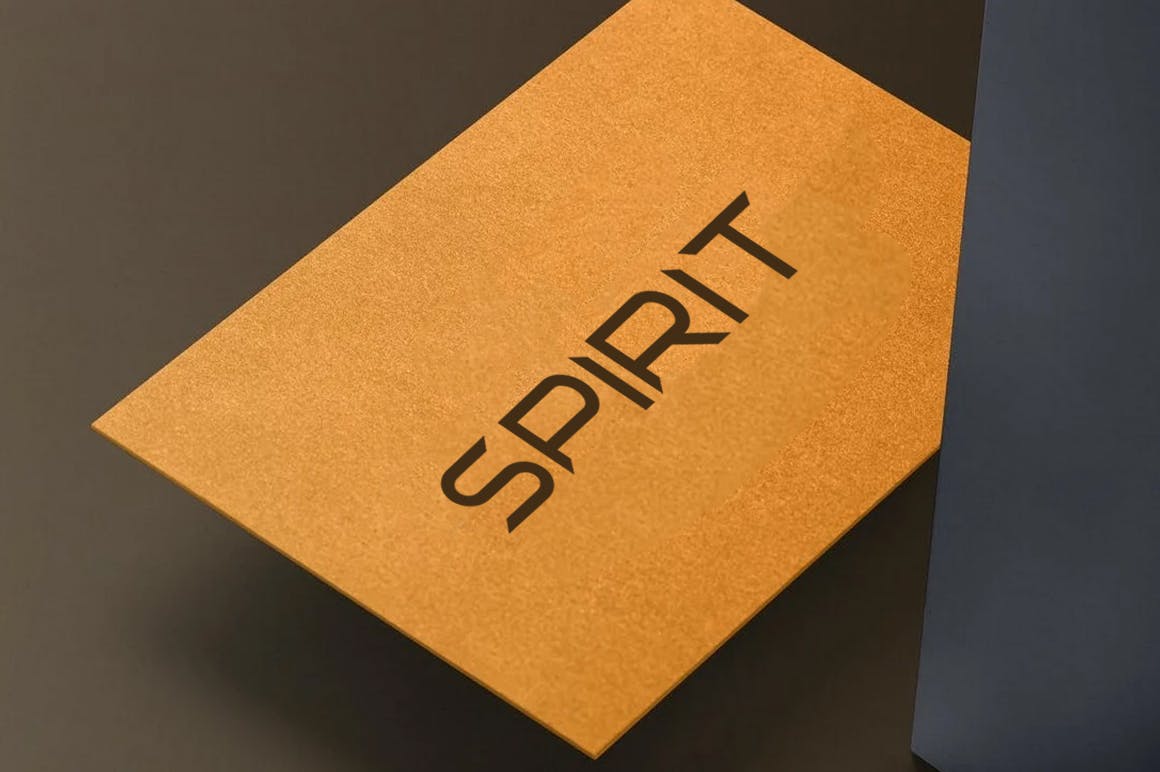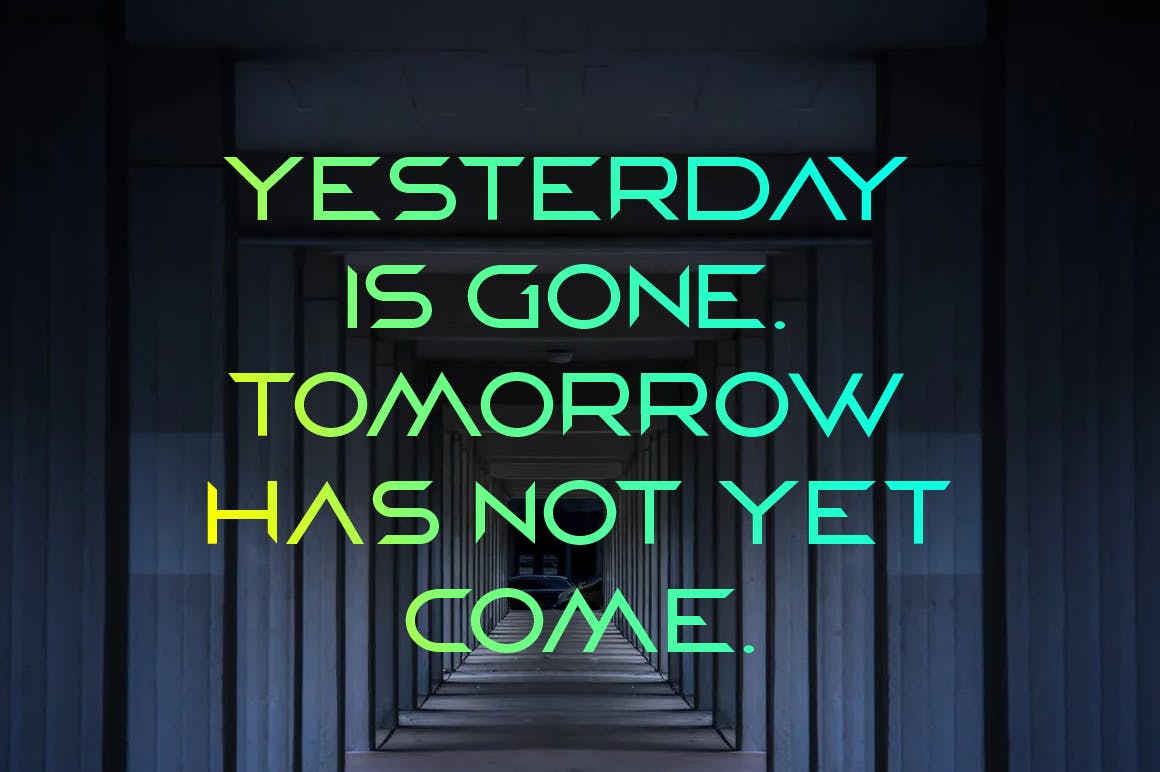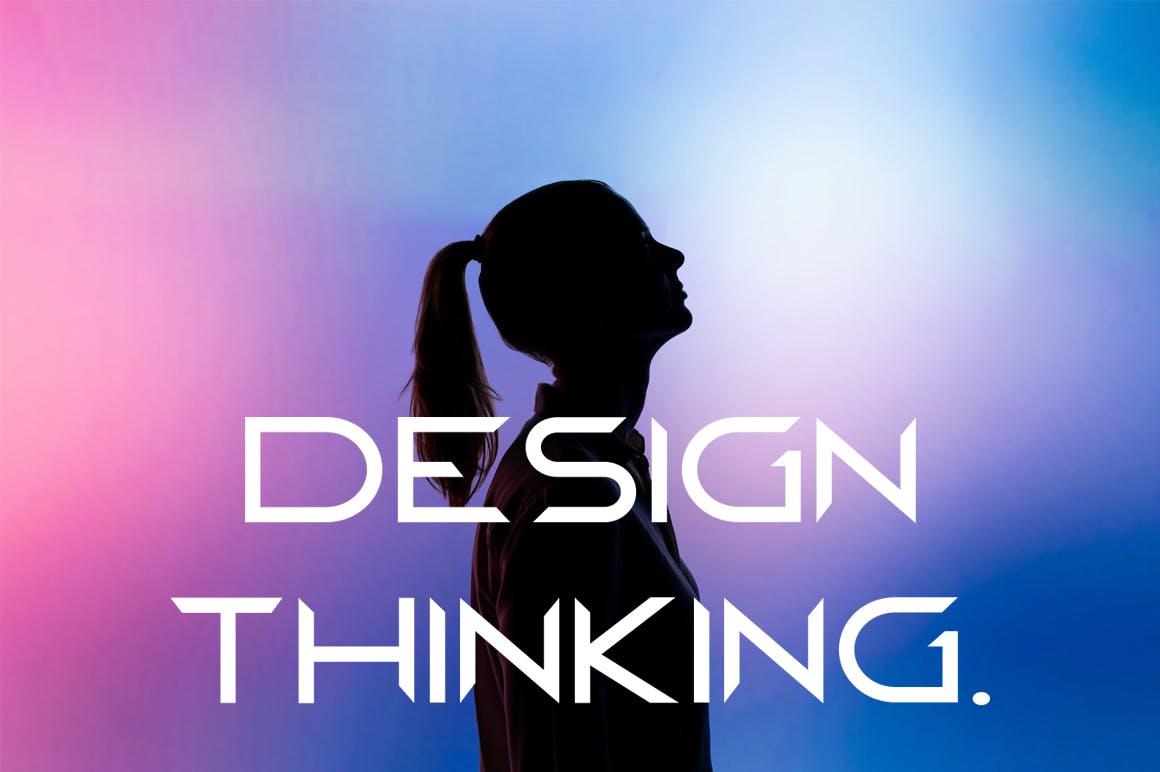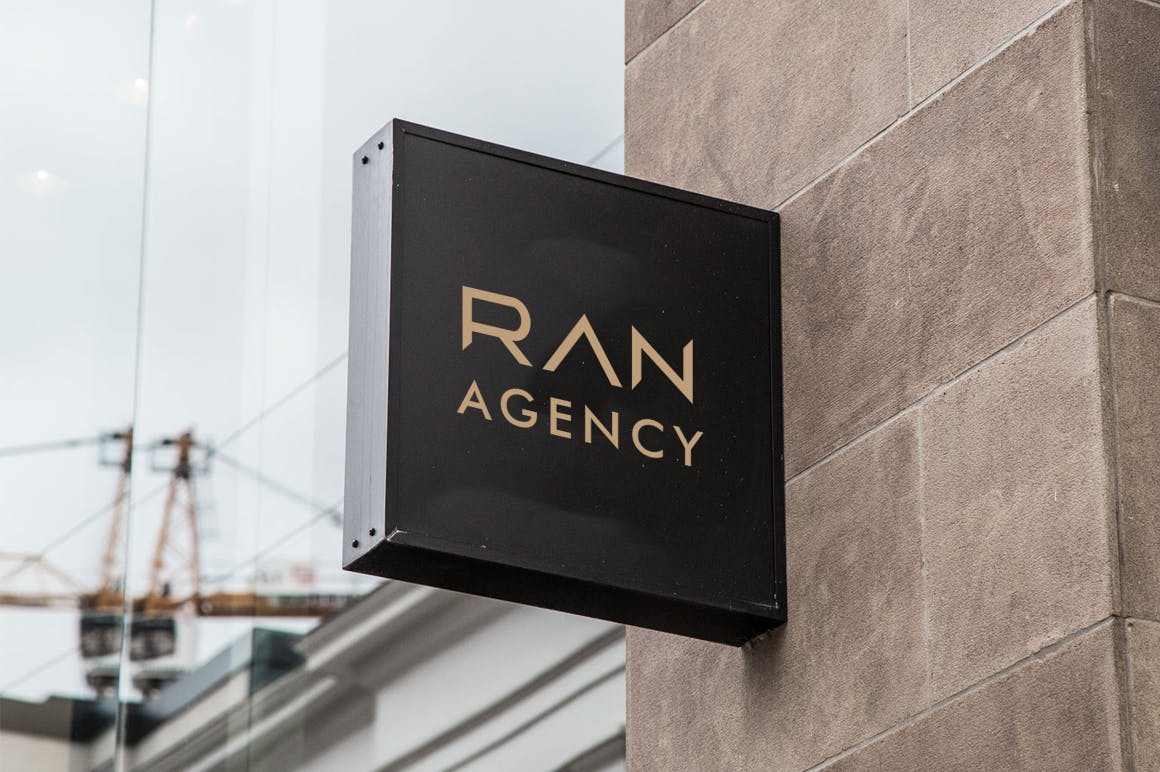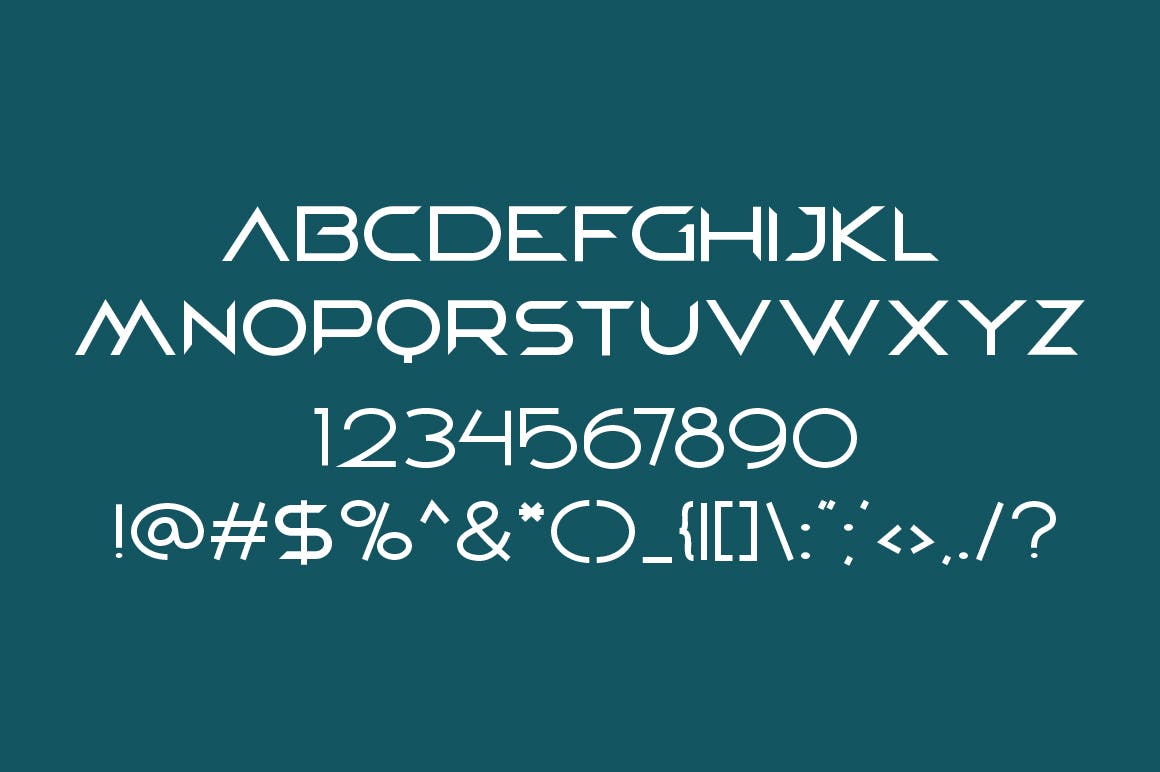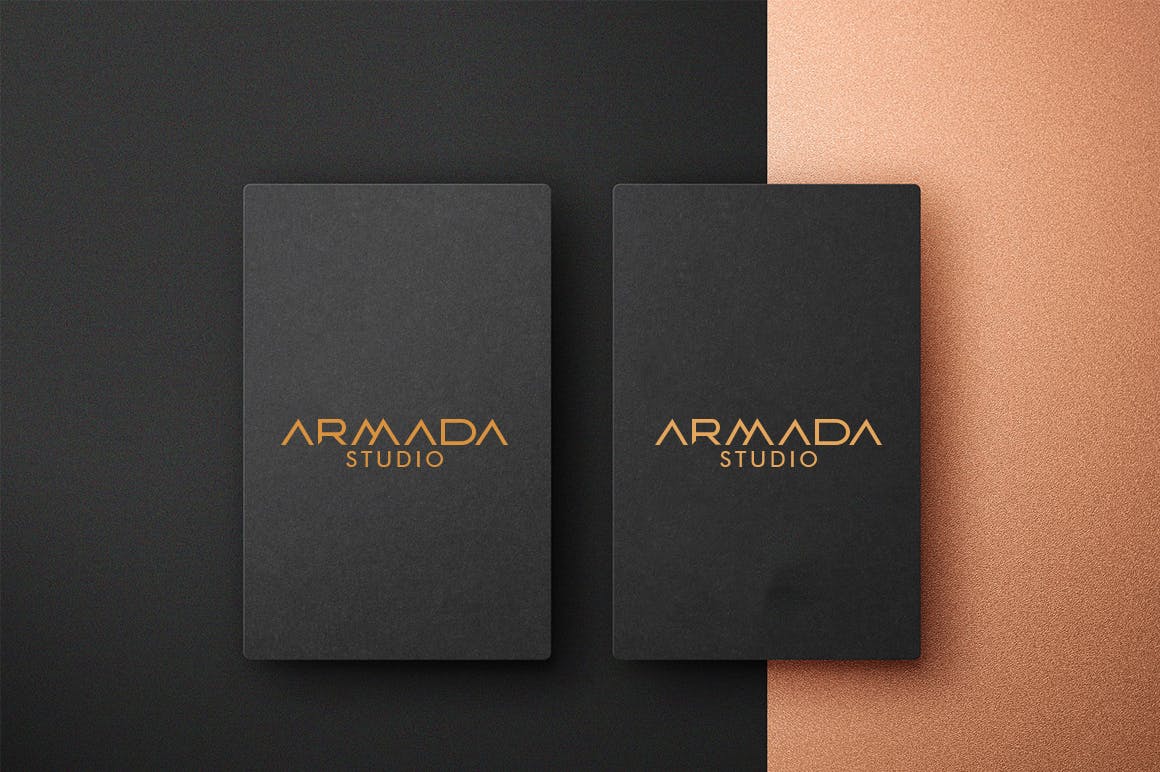
دانلود فونت مدرن دلتا | مناسب برای طراحی‌های آینده‌نگر
Deltha Modern Font
فونت دلتا با طراحی منحصر به فرد، گزینه‌ای عالی برای پروژه‌های مدرن شماست.
فونت دلتا یک فونت sans با حروف کوچک منحصر به فرد است که طراحی‌های شما را به حالتی آینده‌نگر و مدرن تبدیل می‌کند. شما می‌توانید از این فونت برای هر نوع پروژه‌ای استفاده کنید، به‌ویژه برای ایجاد لوگوتایپ.
ویژگی‌ها:
• حروف بزرگ و کوچک
• اعداد
• نقطه‌گذاری و نمادها
• پشتیبانی چندزبانه